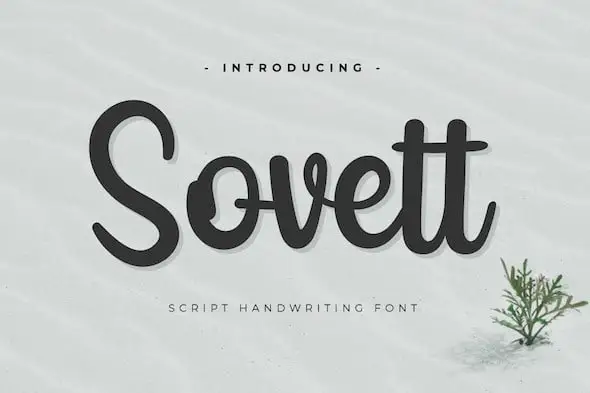
A Sovett Script Font é uma elegante opção para designers que buscam criatividade e sofisticação em seus projetos digitais. Desenvolvida por twinletter, essa fonte script flexível oferece a liberdade de personalização necessária para transformar qualquer design num trabalho excepcional. Seu charme genuíno é perfeito para quem busca uma fonte que ressalte seu texto sem perder sua autenticidade. A Sovett Script é ideal para criar mensagens memoráveis, seja em materiais impressos ou no ambiente digital. Com sua escrita curvilínea e delicada, essa fonte irá tornar seus projetos ainda mais profissionais e atraentes.